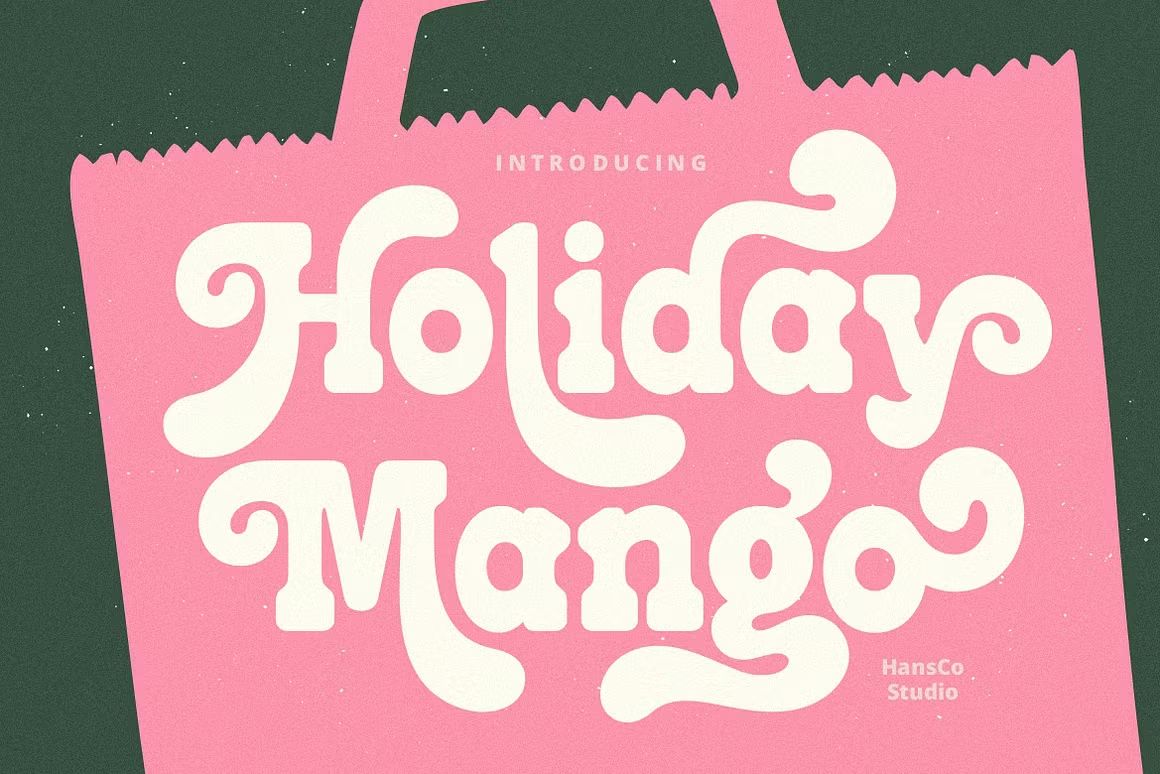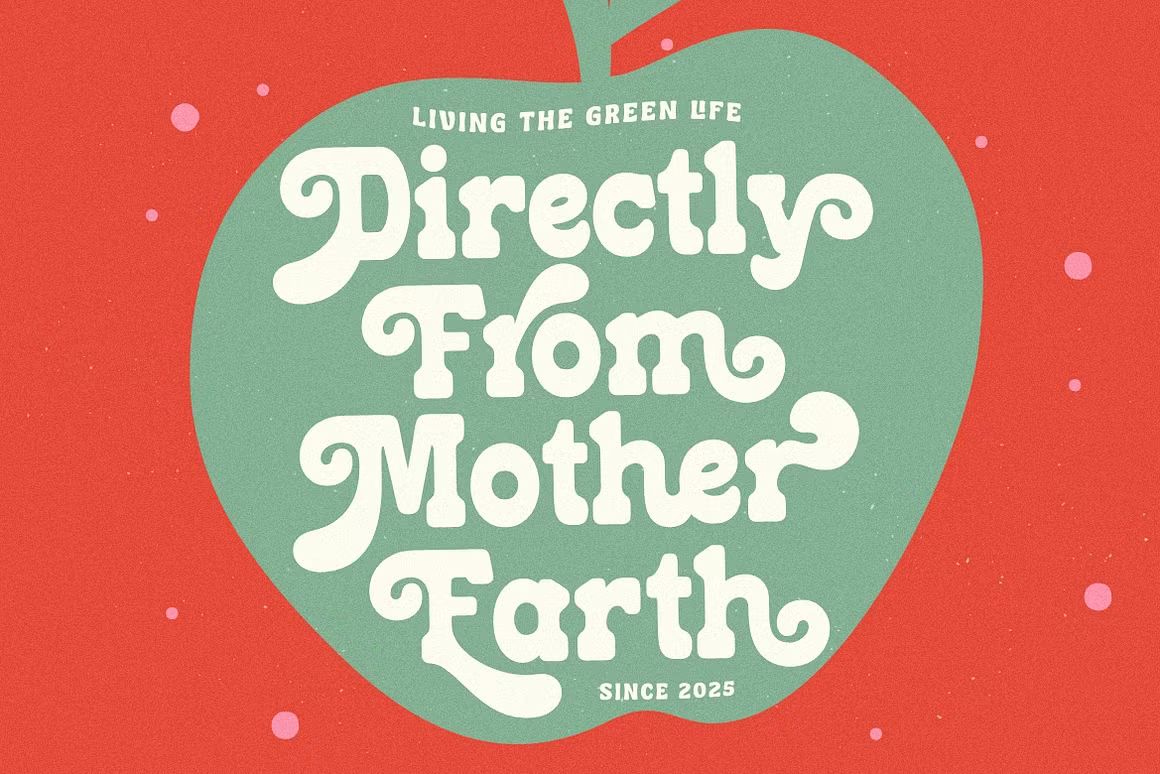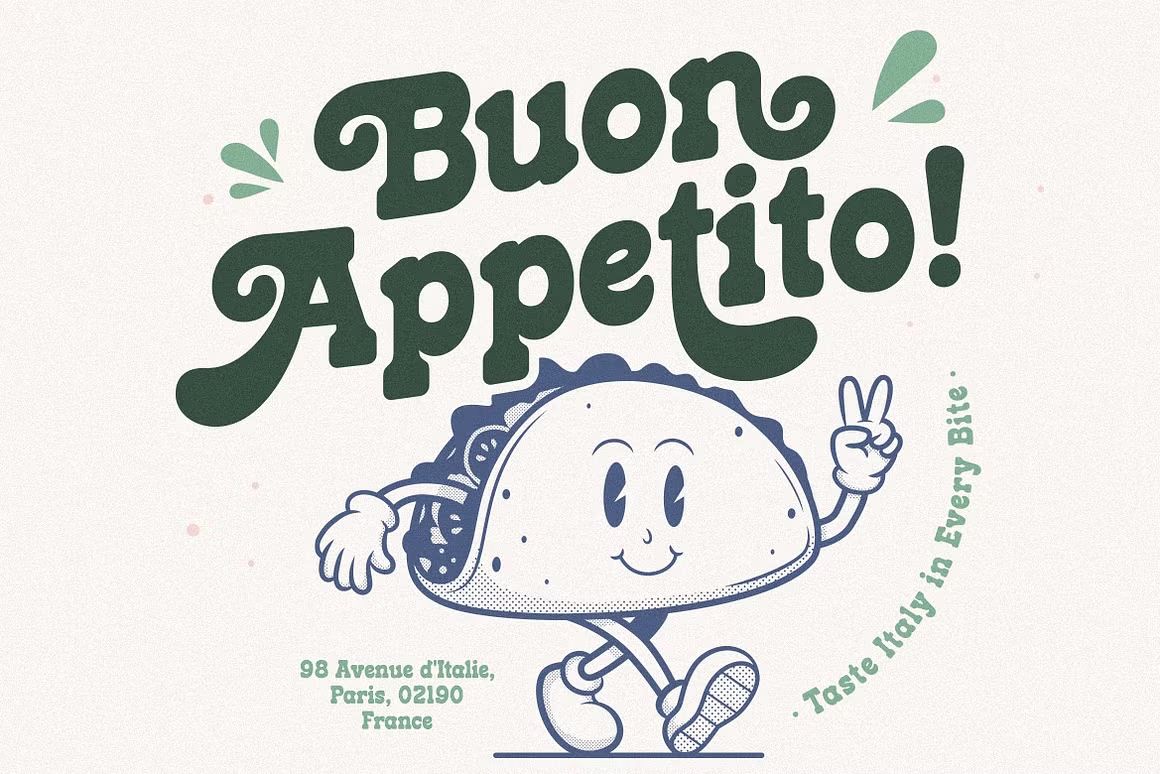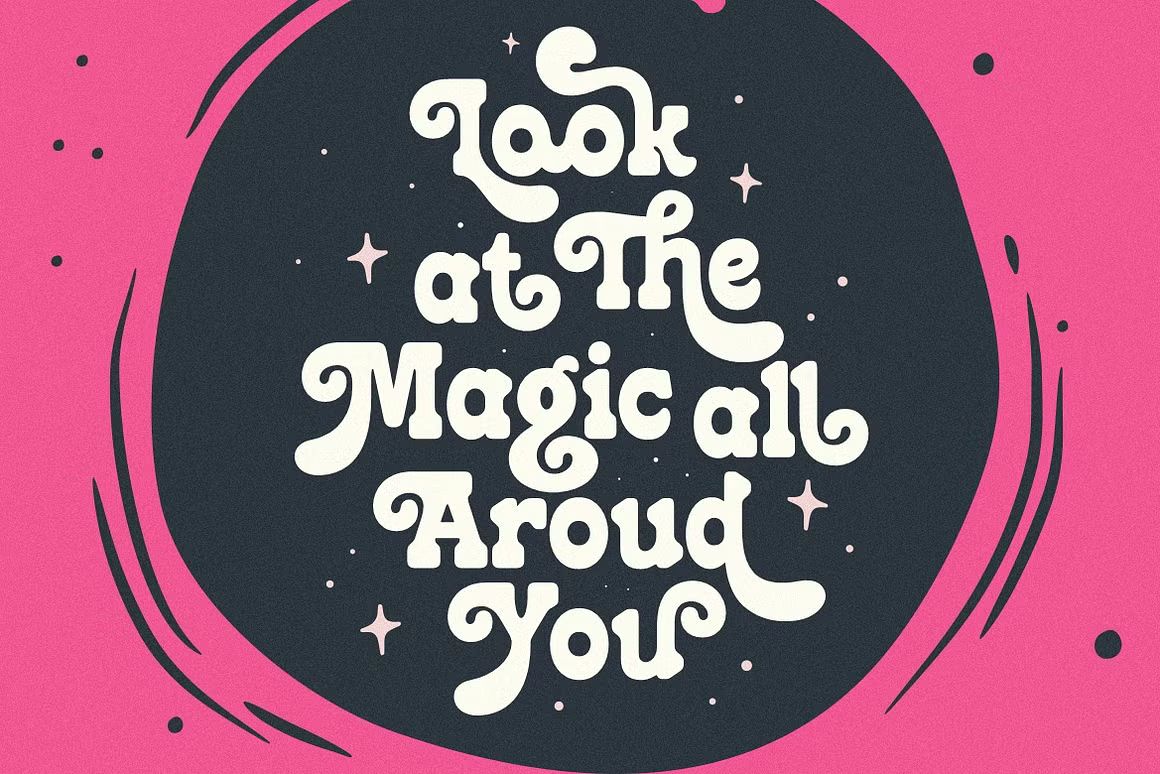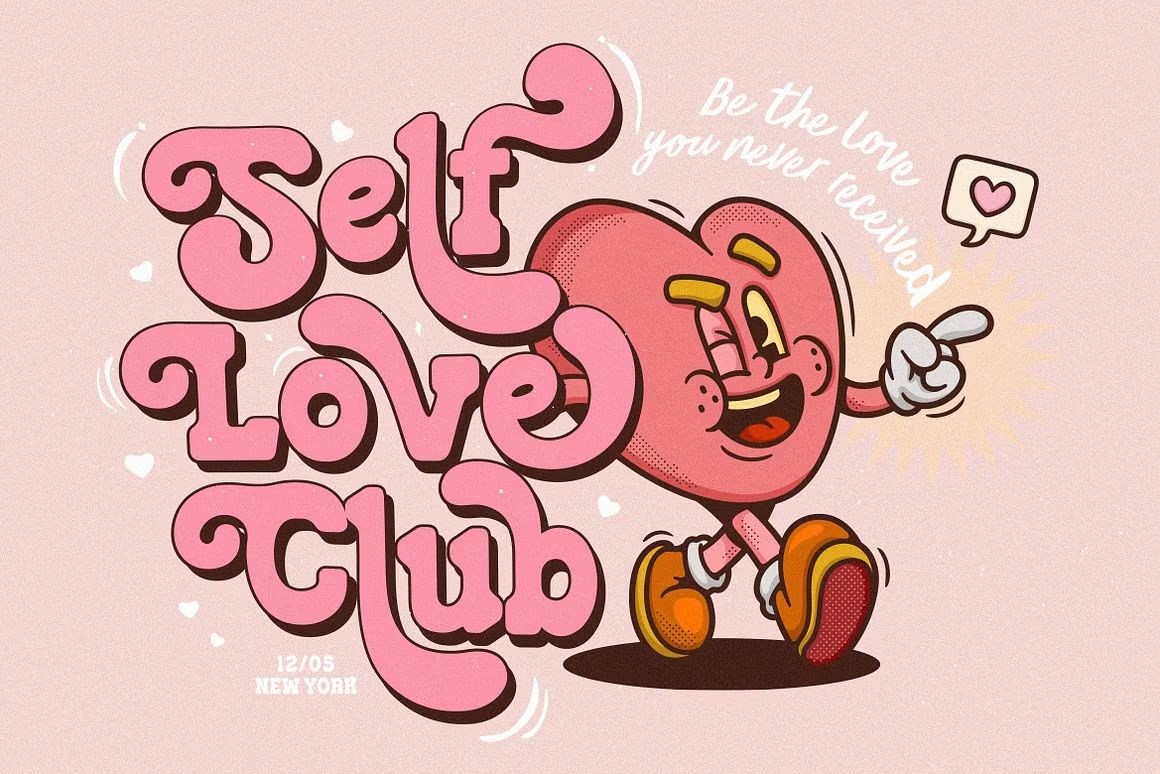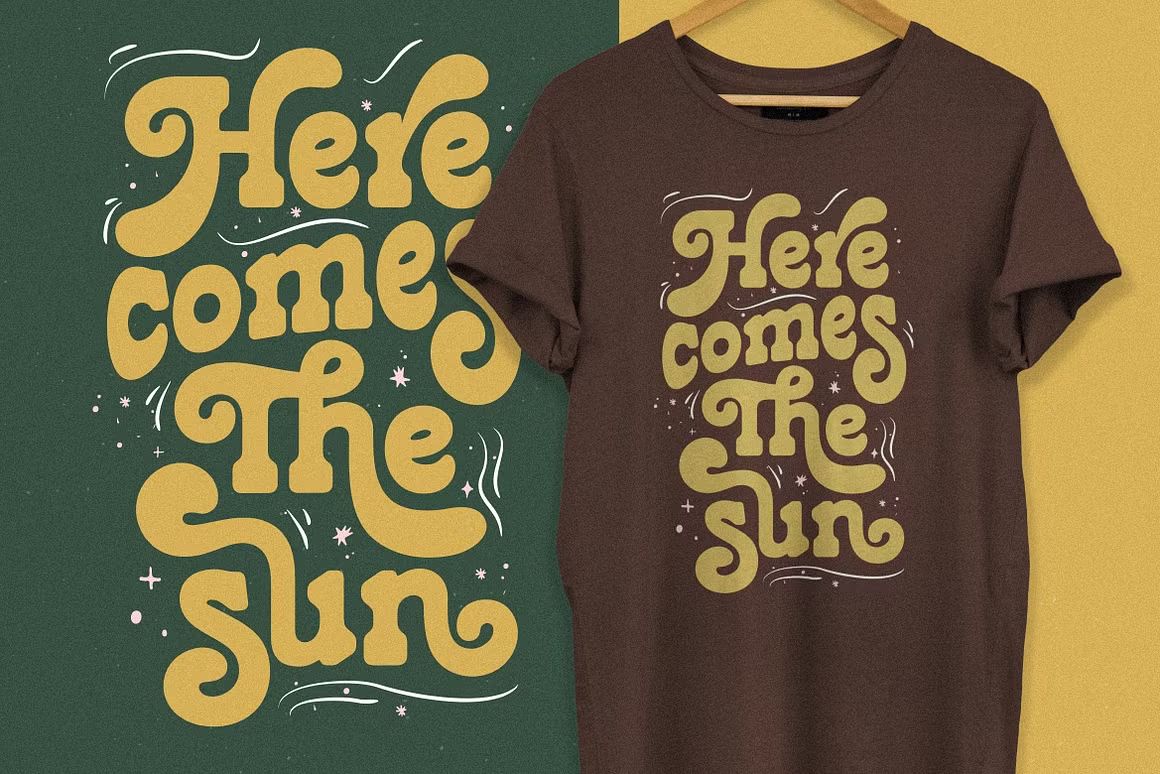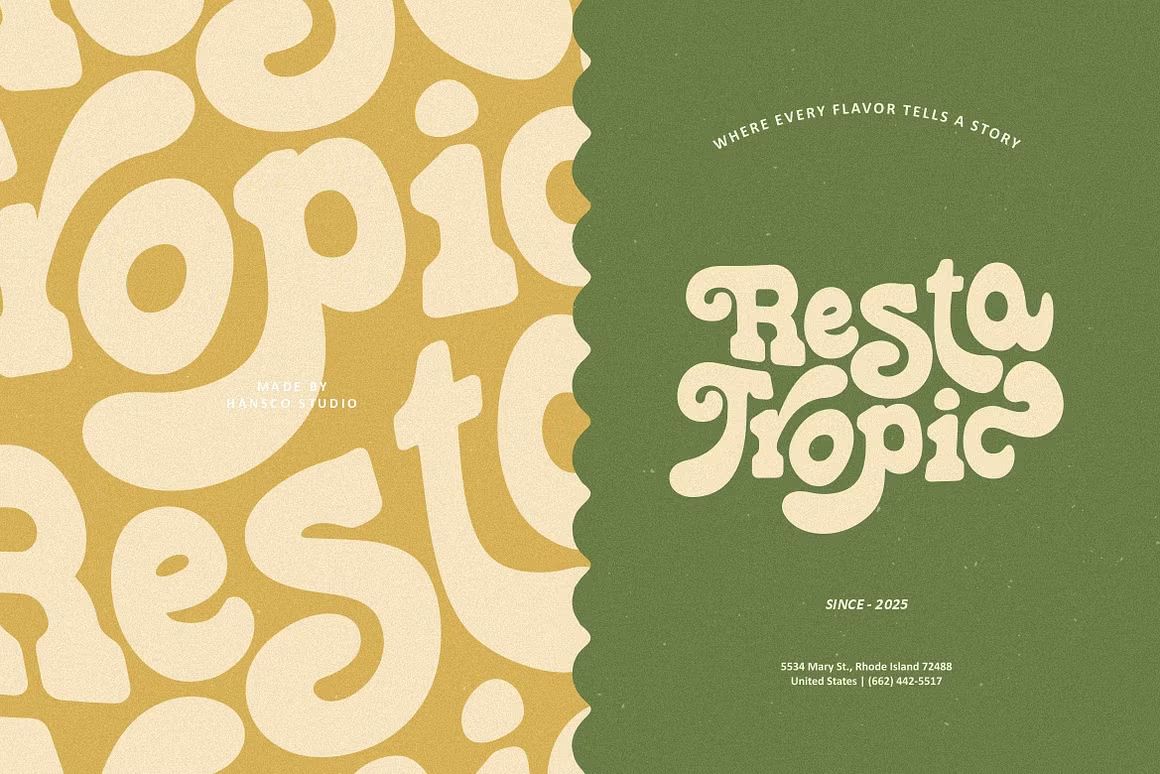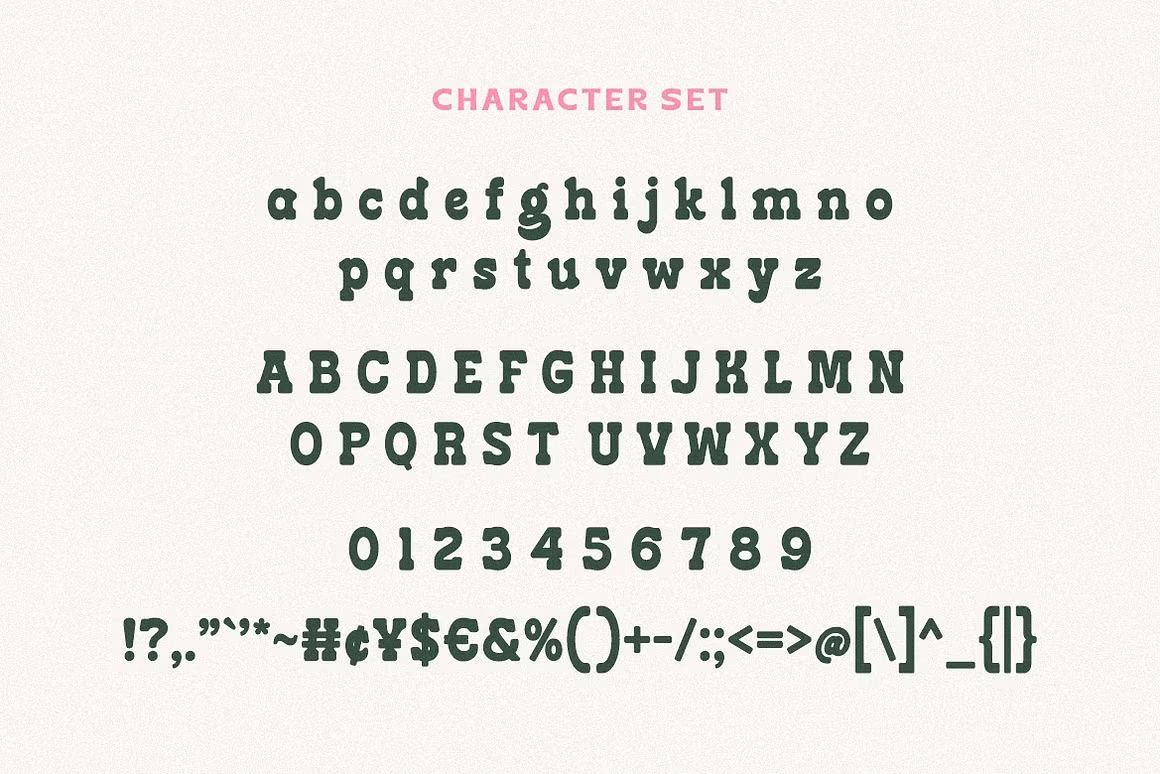
Holiday Mango – Sans Serif Font
Holiday Mango adalah font sans serif dengan nuansa fun, segar, dan kasual. Menggabungkan bentuk huruf yang bulat, ramah, dan modern, font ini cocok untuk desain bertema liburan, makanan & minuman, kemasan produk, branding lifestyle, hingga konten media sosial yang ceria dan berwarna. Tampilan yang playful namun tetap rapi menjadikan Holiday Mango ideal untuk berbagai proyek kreatif.
• Sans serif bergaya fun dan kasual
• Cocok untuk branding, packaging, dan desain bertema liburan
• Termasuk huruf besar, kecil, angka, dan simbol